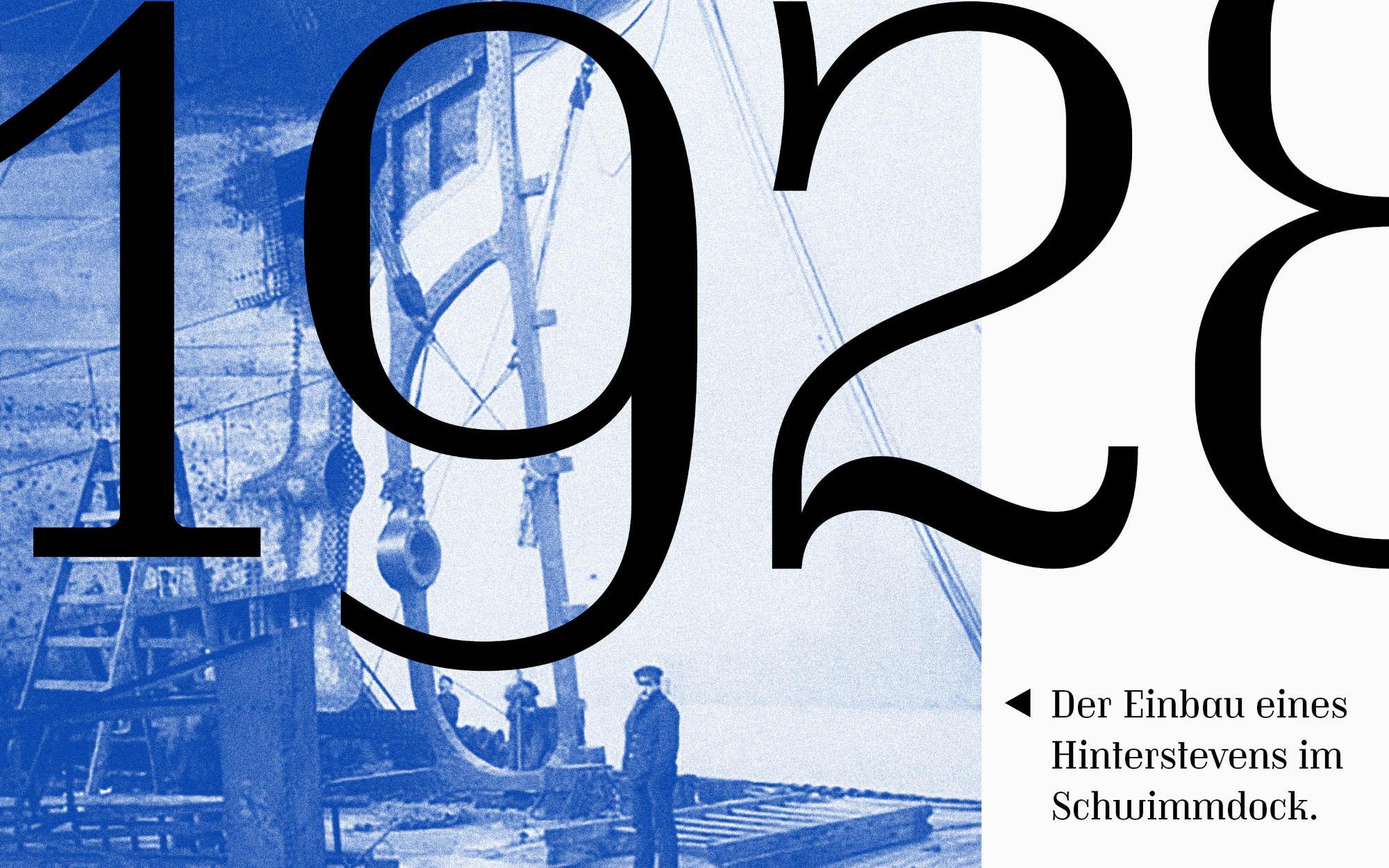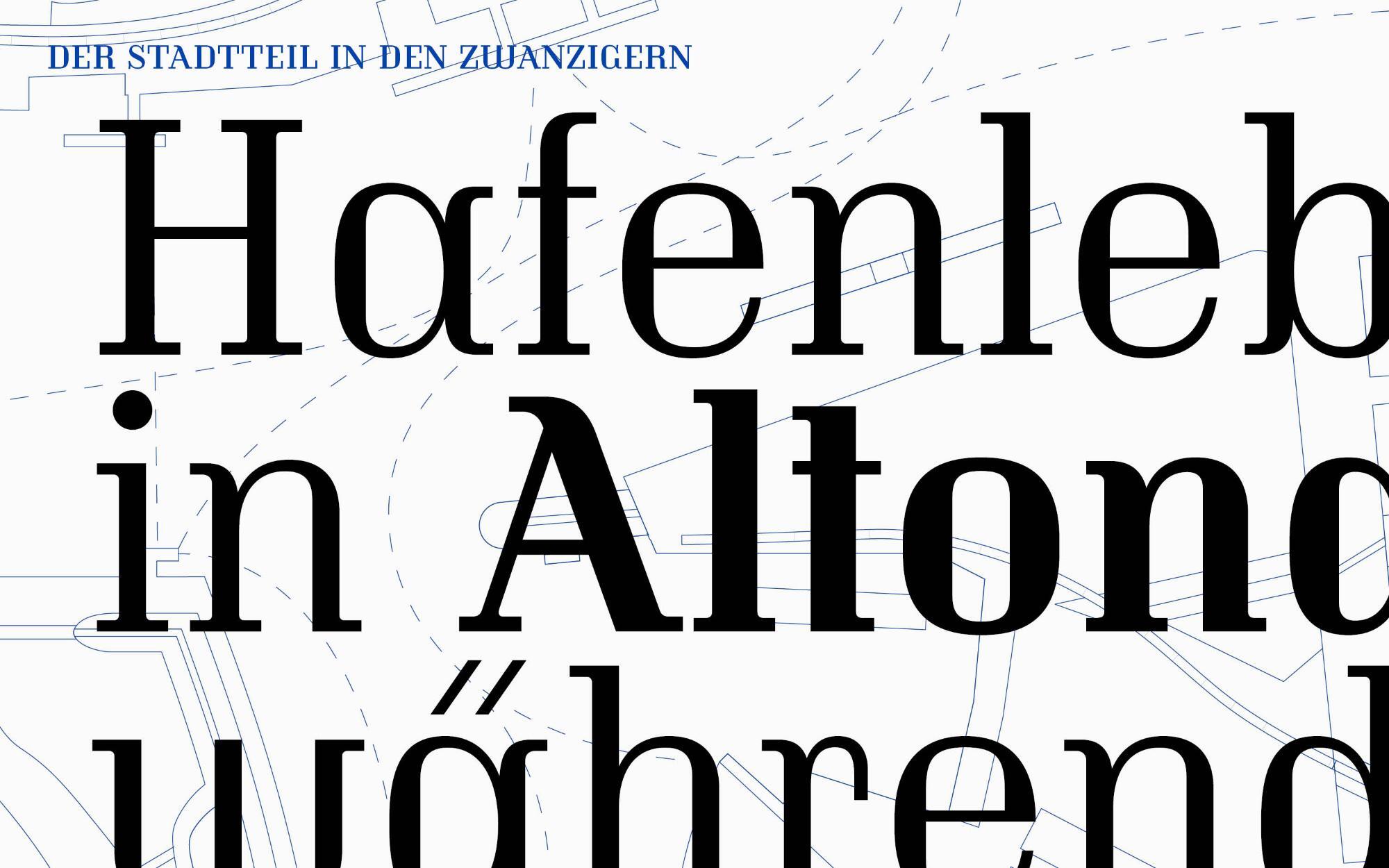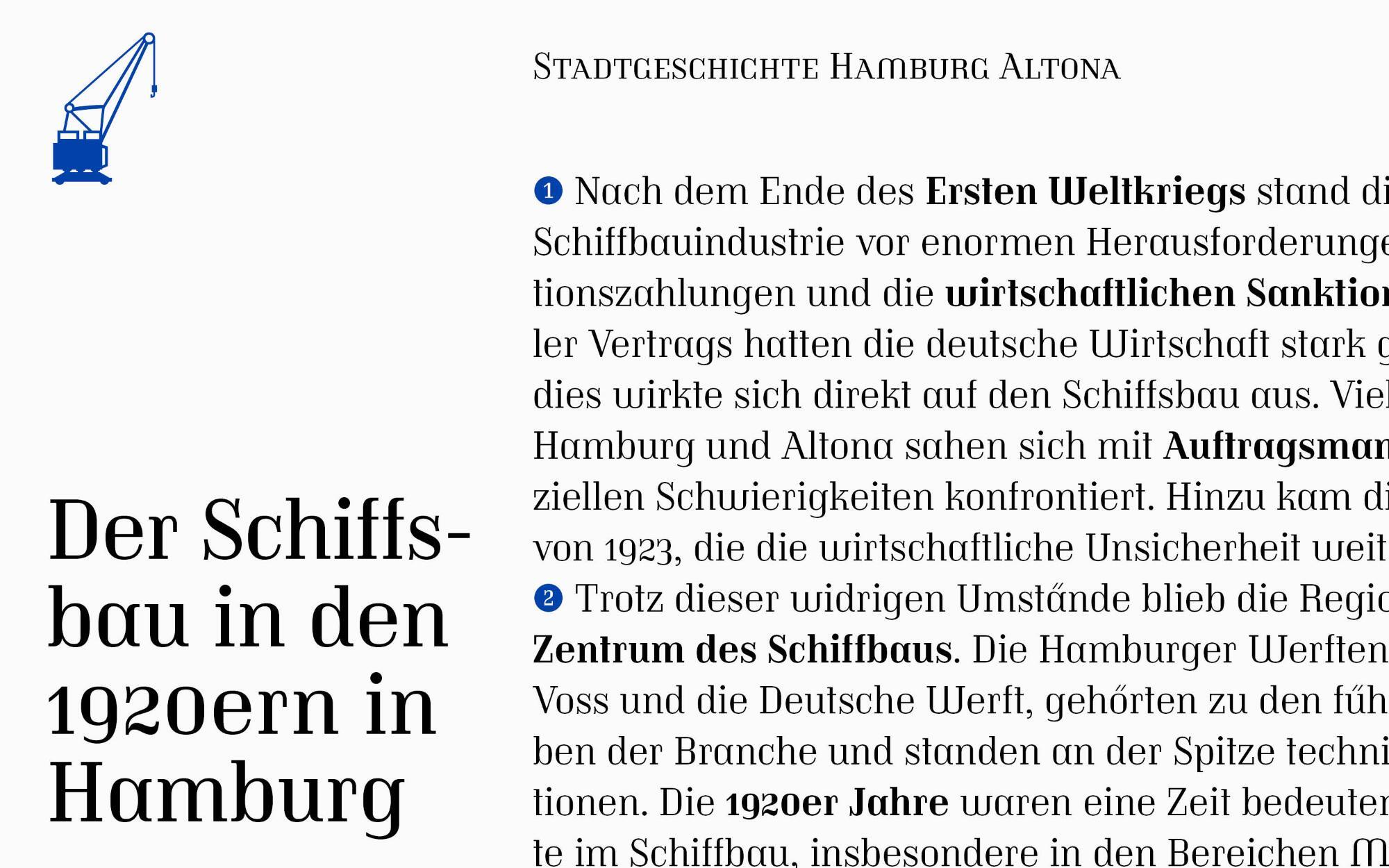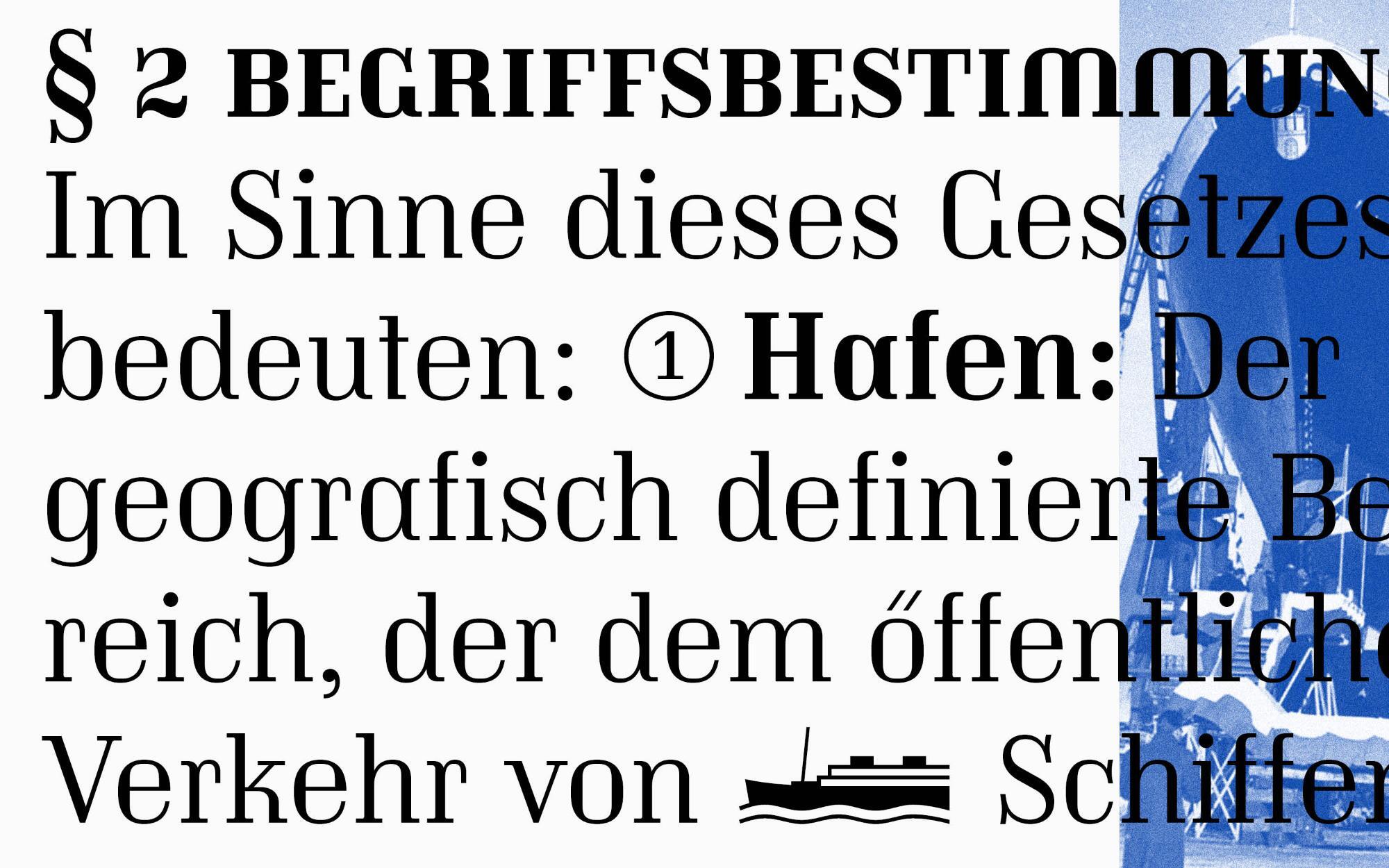
- Antiqua geometrisch
- Versaleszett:
- enthalten
Die Altona von Albert-Jan Pool, Julia Uplegger und Antonia Cornelius geht auf eine Schrift zurück, die in den 1920er und 30er Jahren auf Straßenschildern im damals noch selbstständigen Altona bei Hamburg verwendet wurde. Noch heute sind einige wenige Schilder zu finden, woraus die Idee einer Neuinterpretation entsprang.
Die geometrische Antiqua verfügt über fünf Strichstärken (Light—Black), die auch als Variable Font erhältlich sind. Der breit ausgebaute lateinische Zeichensatz verfügt über mehr als 1200 Glyphen, darunter auch Kapitälchen. Zahlreiche stilistische Varianten, wie Zierbuchstaben oder alternative Brüche als Stacked Fractions, bieten einen breiten Gestaltungsspielraum. Mit dem Stylistic Set bzw. Formatsatz »German Capital Sharp S« (Stylistic Set 13 bzw. Satz 13) erhält man statt dem Doppel-S das Versaleszett (ẞ).
Zusammen mit der Altona erschien die Alison (Text & Head) von Julia Uplegger. Sie ist als „Enkelin“ zu verstehen, die die rund 100 Jahre alte Altona ins heutige 21. Jahrhundert übersetzt: eine elegante klassizistische Antiqua mit ähnlich stringenten Zügen. Beide Schriftfamilien sind genau aufeinander abgestimmt und für den Einsatz Seite an Seite gestaltet.